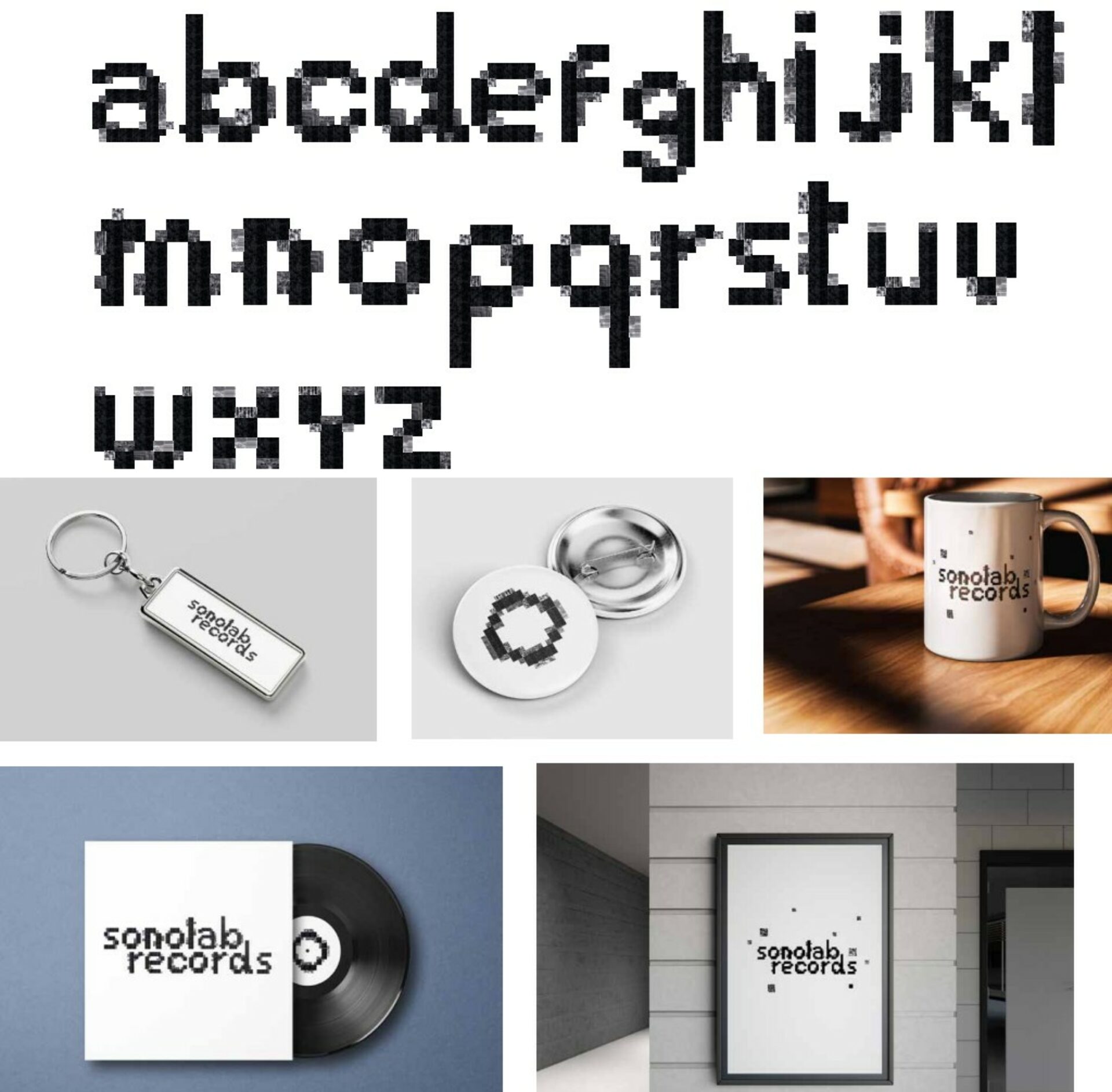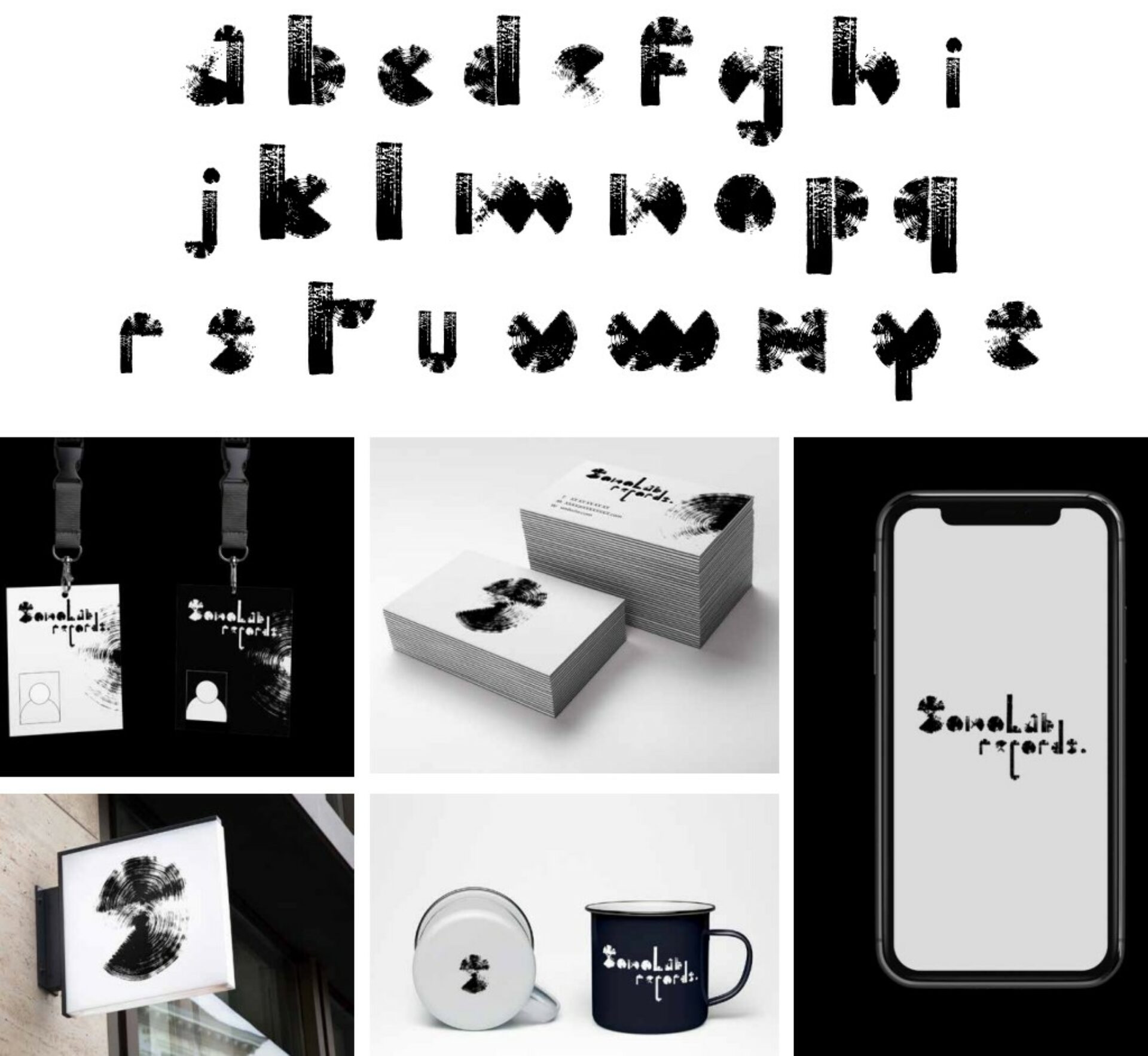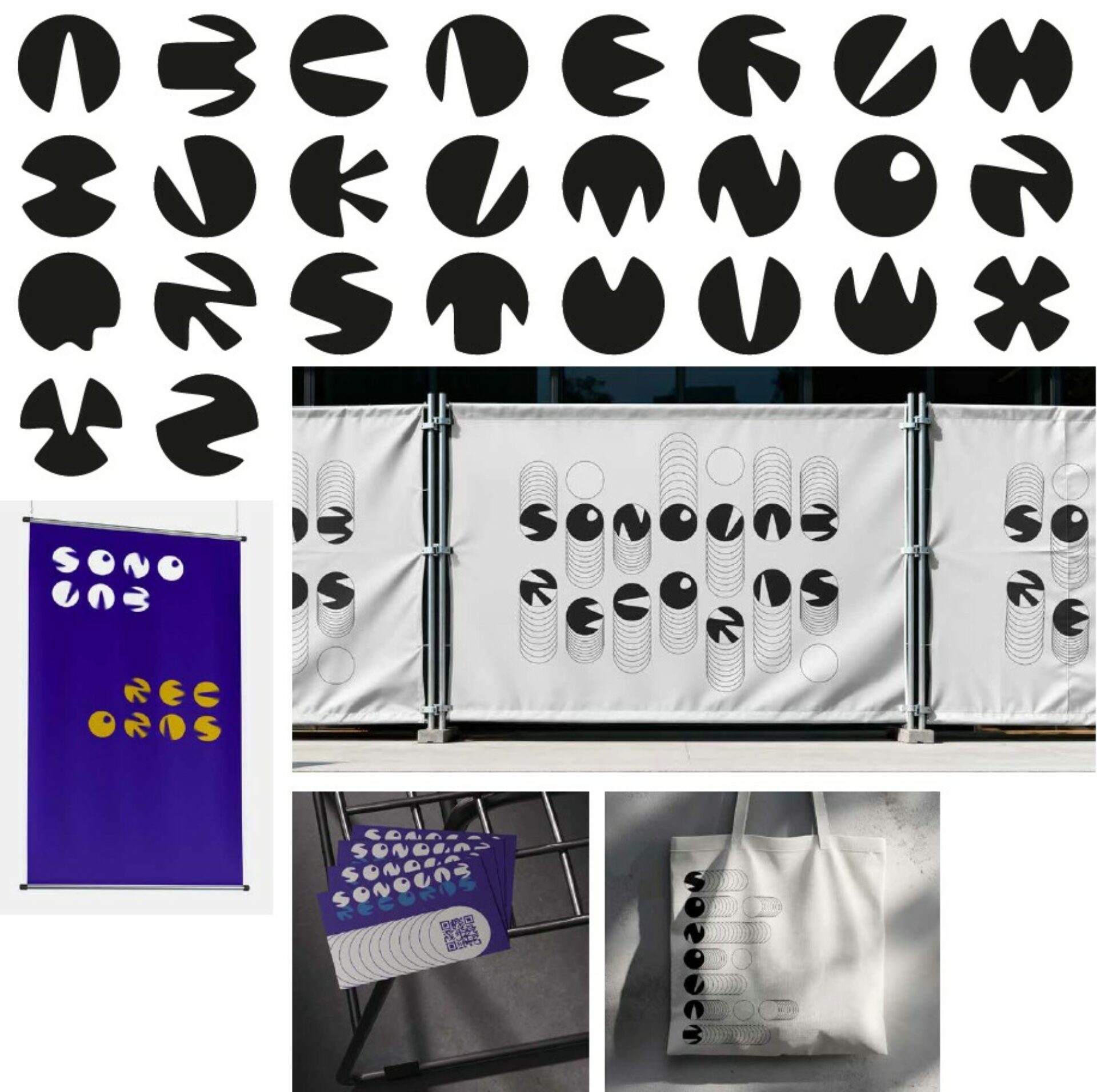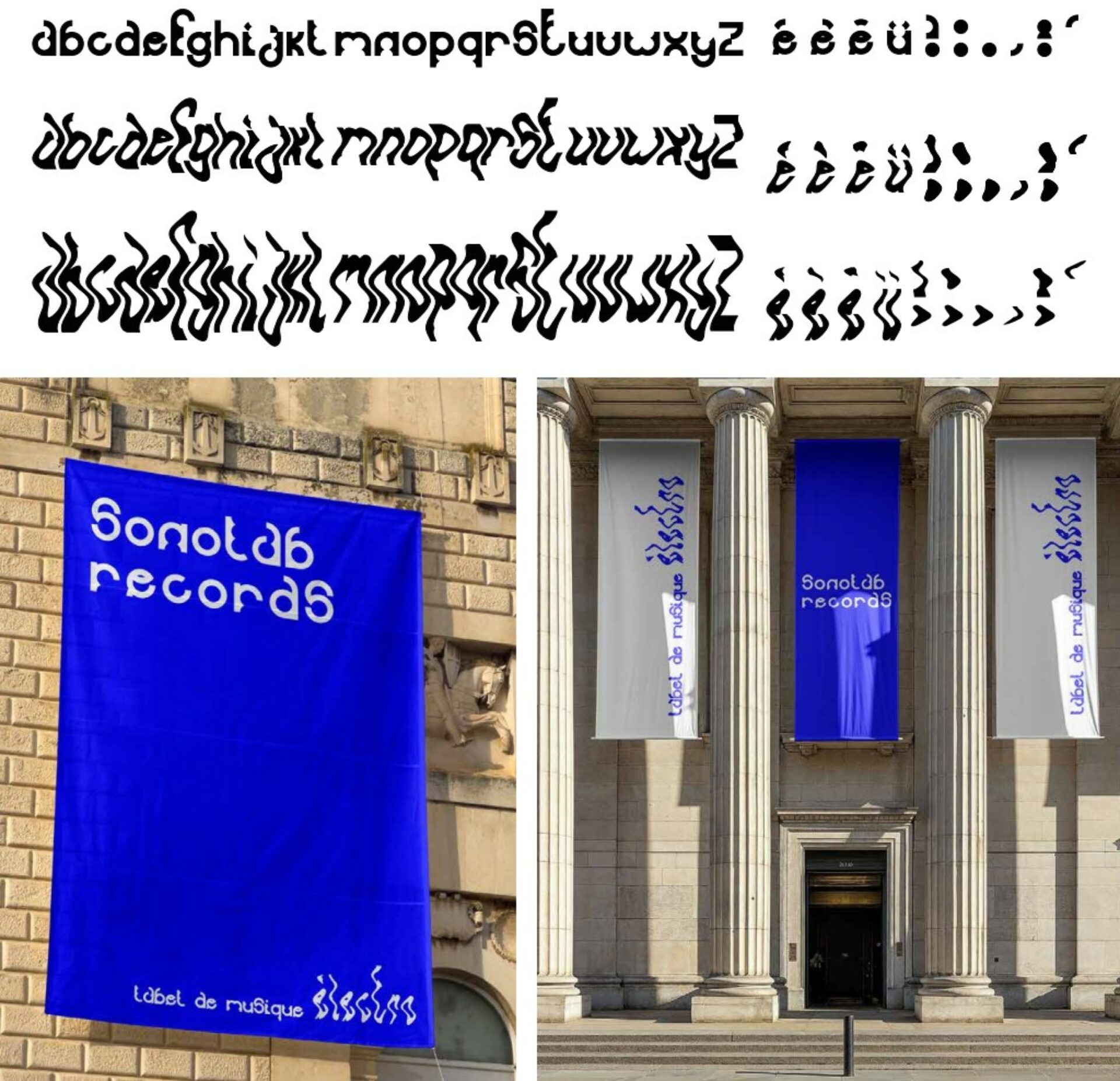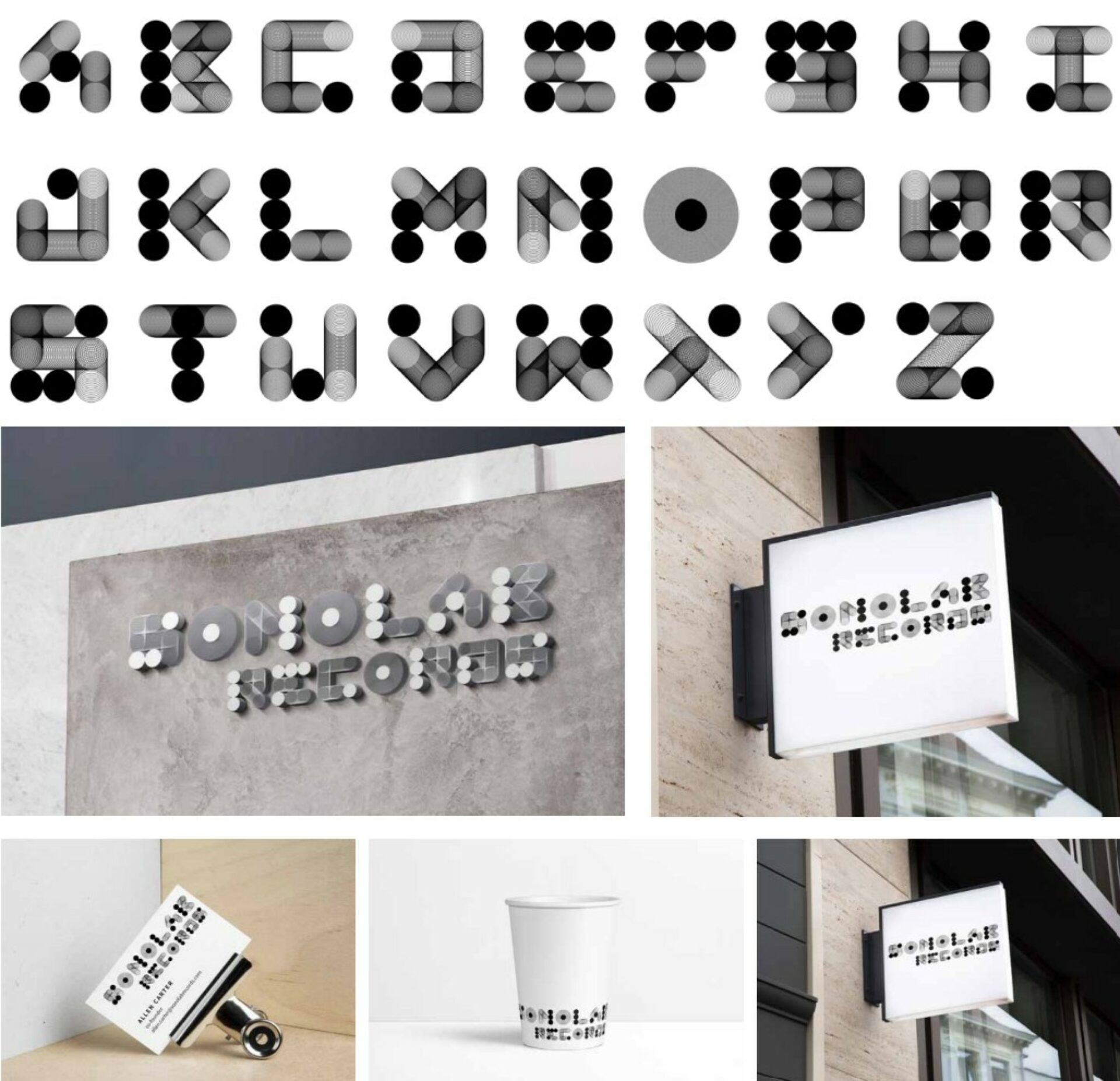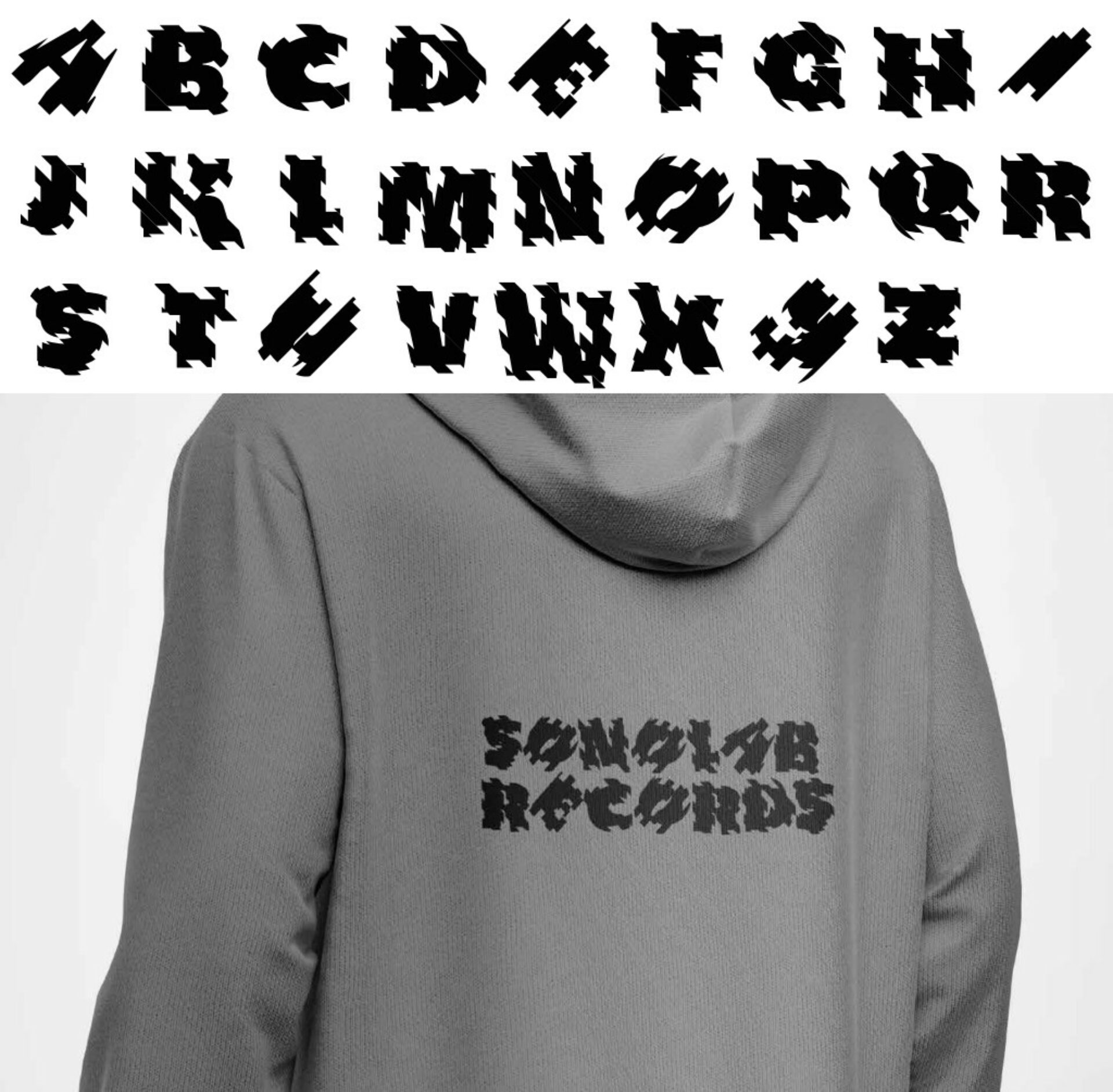
Projet étudiant Cycle Professionnel Design Graphique 1ere année
Présentation du projet
Comment traduire l’énergie, la diversité et l’expérimentation propres à la musique électronique à travers la typographie ?
C’est le point de départ du projet Sonolab Records, un nouveau label (fictif) dédié à la découverte de talents dans l’univers éclectique des musiques électroniques. Les étudiants du Cycle Pro Design Graphique en 1re année ont été invités à concevoir l’identité typographique de la marque, en développant une écriture visuelle capable d’incarner son positionnement artistique.
Dans un secteur où l’image joue un rôle central, la typographie devient ici un véritable territoire d’expression : rythme, modularité, vibration, structure et rupture composent le langage graphique de Sonolab.
Sujet de l’exercice
L’exercice consistait à concevoir une typographie modulaire originale pour la marque Sonolab Records.
Les étudiants devaient imaginer un système de lettres capable de :
- refléter la richesse et l’éclectisme de la musique électronique,
- fonctionner comme une signature forte et identifiable,
- s’adapter à différents supports (affiches, pochettes, supports digitaux)
La contrainte principale reposait sur la notion de modularité : créer un alphabet structuré à partir d’éléments répétables, combinables ou transformables, permettant de générer des variations tout en conservant une cohérence formelle.
Objectifs pédagogiques
Ce projet avait pour ambition d’initier les étudiants à la création typographique comme outil central d’identité visuelle.
Ils ont été amenés à :
- traduire graphiquement un univers musical en langage typographique,
- développer une identité cohérente et forte à partir d’un principe formel clair,
- comprendre la construction d’un système graphique modulaire,
- expérimenter la relation entre forme, rythme et perception visuelle.
L’exercice visait également à renforcer la méthodologie créative : recherche, esquisses, tests formels, ajustements et déclinaisons.
Techniques utilisées
Pour développer leurs propositions, les étudiants ont mobilisé :
- Photoshop
- Illustrator
- Fontself
- ainsi que des techniques traditionnelles (croquis, expérimentations manuelles).
À travers Sonolab, les étudiants ont exploré la typographie comme terrain d’expérimentation graphique, où structure et liberté dialoguent pour créer une identité vibrante et contemporaine.